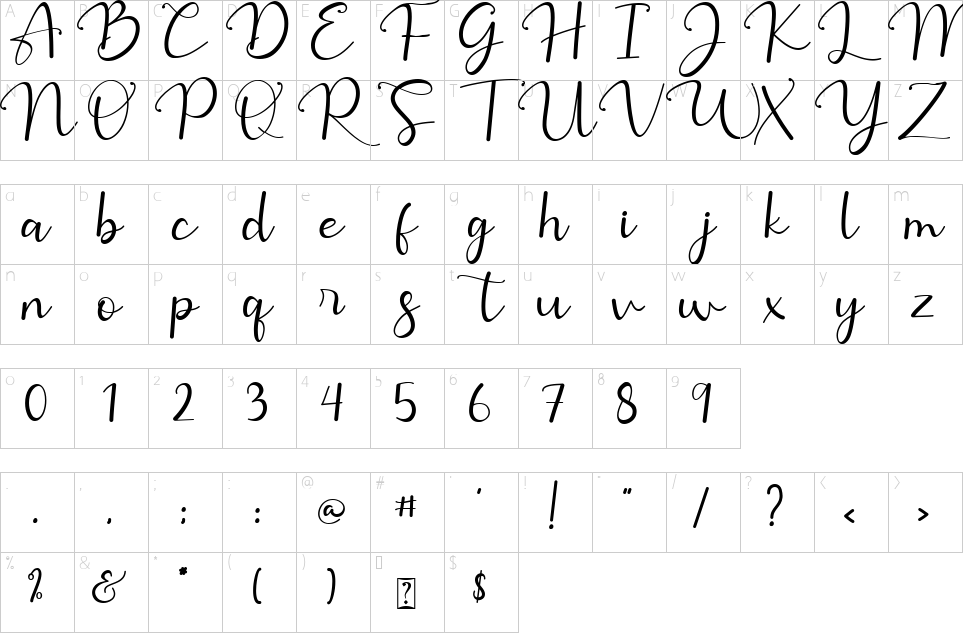
Giette Font – Download Grátis
A fonte Giette é uma opção gratuita para designers e grafistas interessados no design minimalista moderno. Desenvolvida pela AEN Creative Studio, essa fonte oferece um toque sofisticado que se destaca nos projetos digitais. Com seu design limpo e elegante, a Giette adiciona um toque atraente sem comprometer a legibilidade. Esta fonte é especialmente adequada para criações de layout web, materiais gráficos ou até mesmo texturas personalizadas. Com seus downloads registrados em 2,268 vezes, você pode esperar que ela seja uma escolha sólida e confiável para seu trabalho. Seja você um iniciante ou profissional experiente, a Giette é uma fonte gratuita de alta qualidade para quem busca um estilo único em seus projetos digitais.